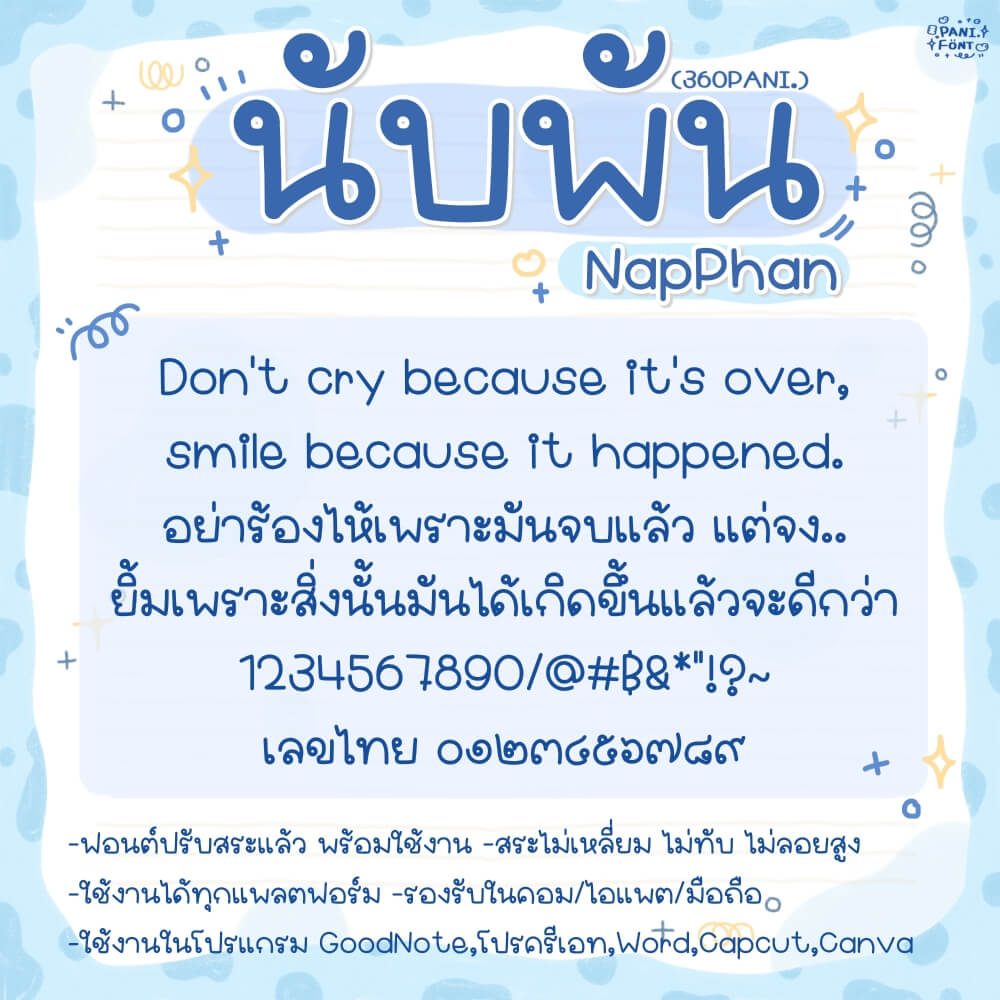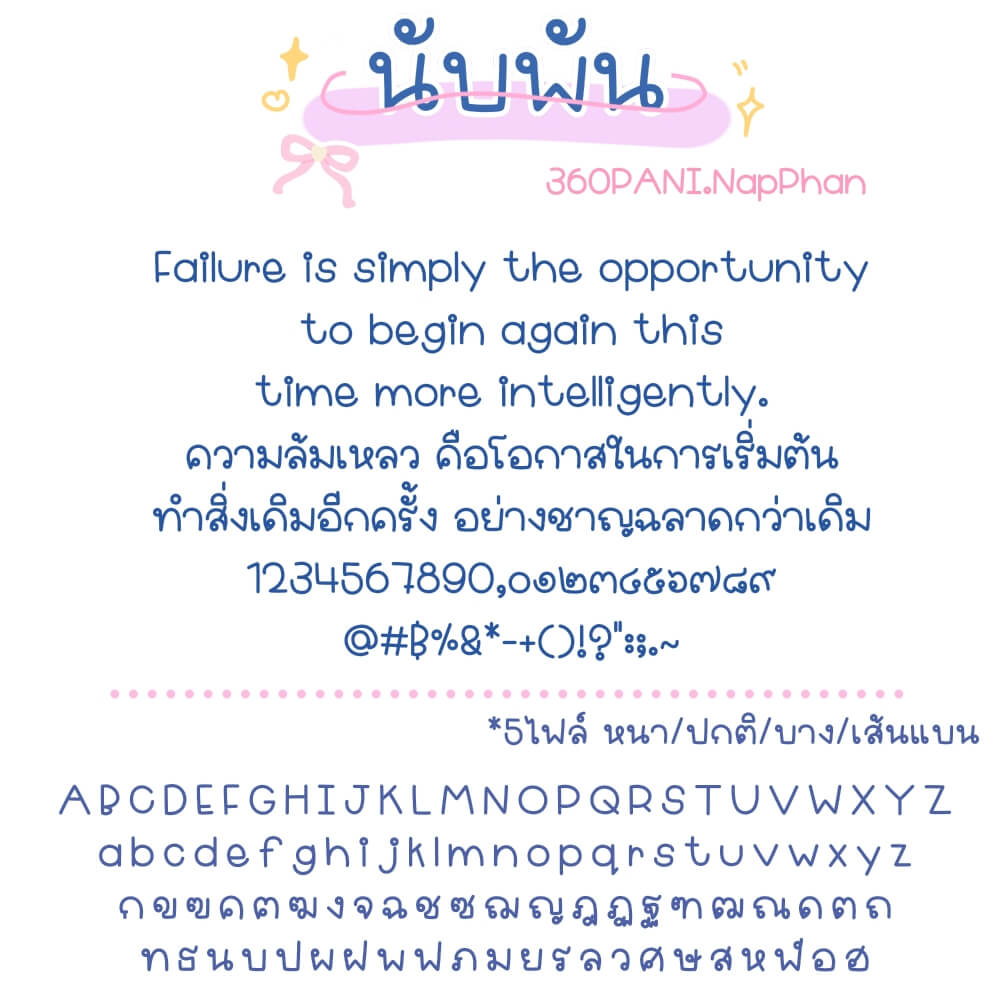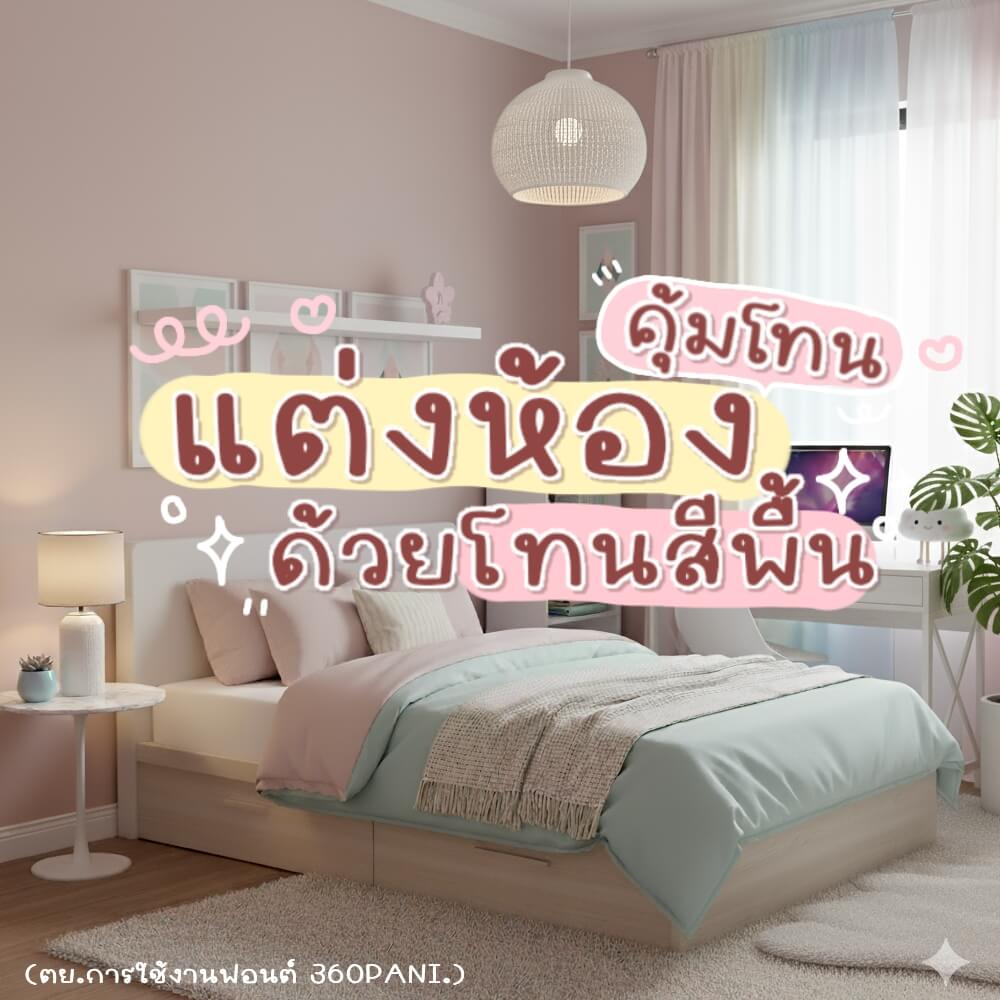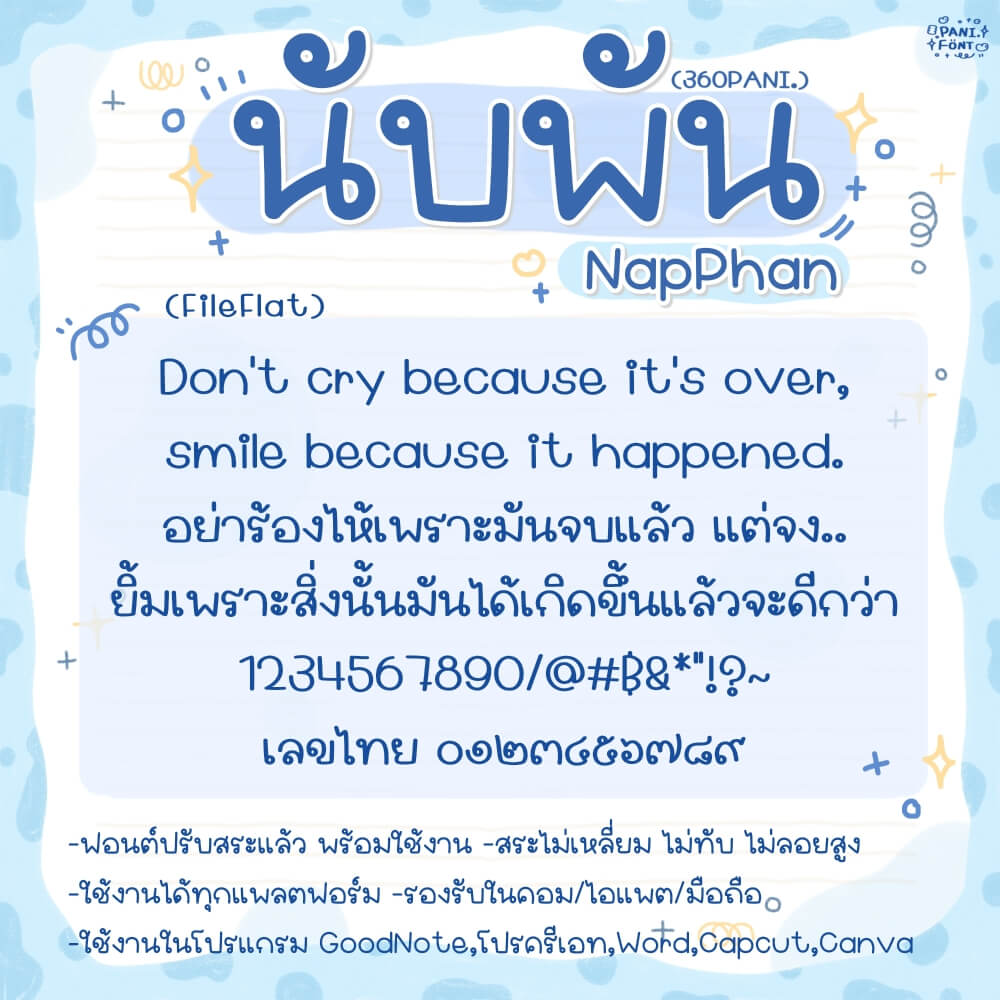
360PANI.นับพัน
ฟอนต์ 360PANI.นับพัน – ฟอนต์หัวกลม แนวเรียบร้อย แต่ยังน่ารัก ใช้จดงานรายละเอียด อ่านง่าย ดูสะอาดตา หรือจะแต่งภาพ แต่งเปิดคลิป ทำสื่อ ทำใบงาน พรินต์งาน ก็เรียบร้อยน่ารัก